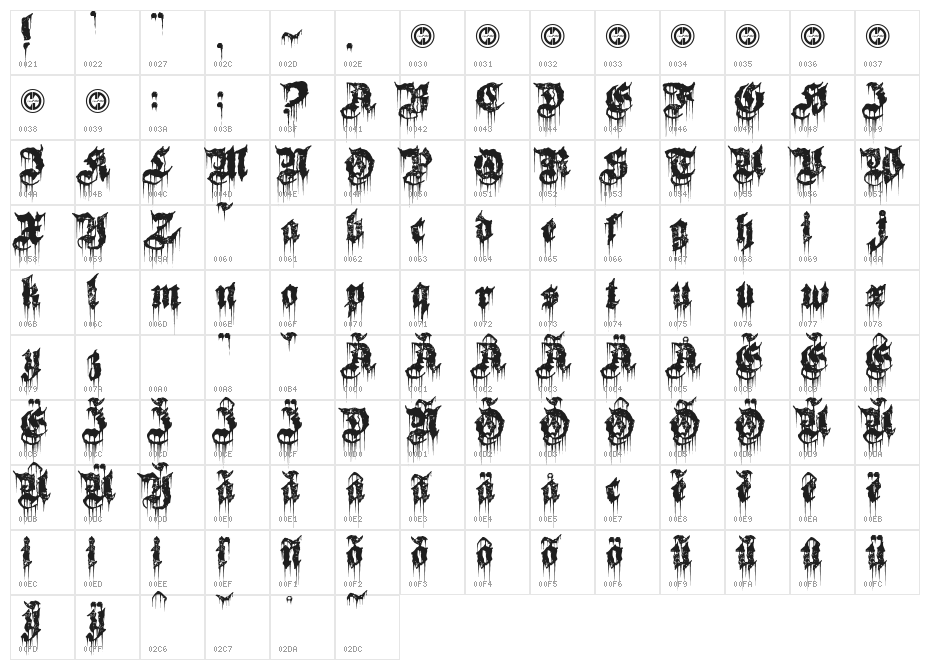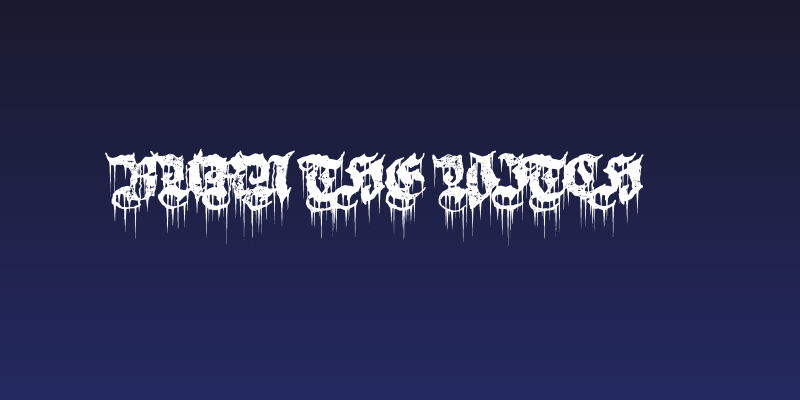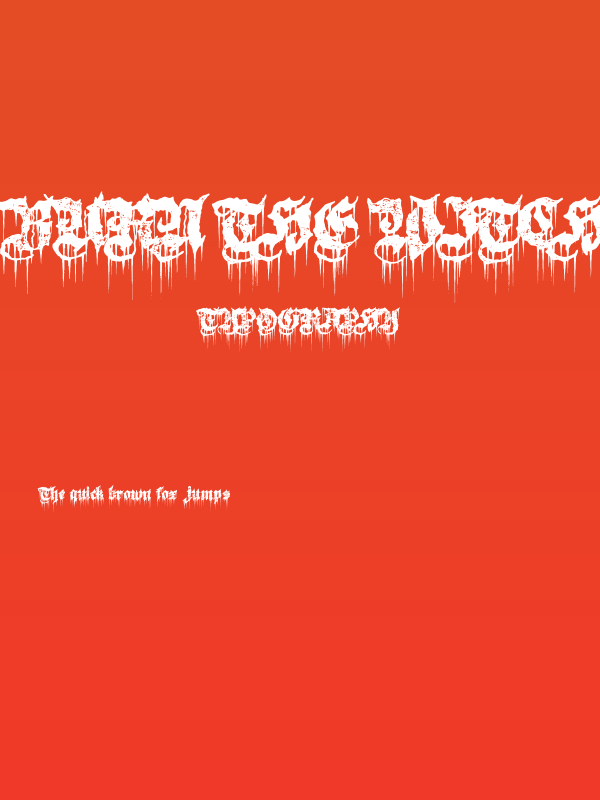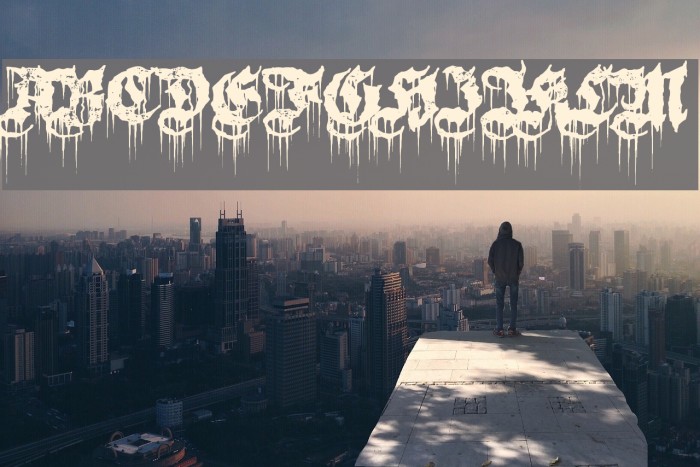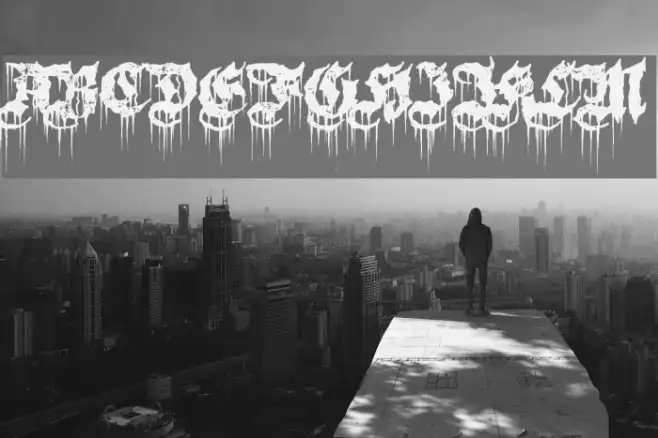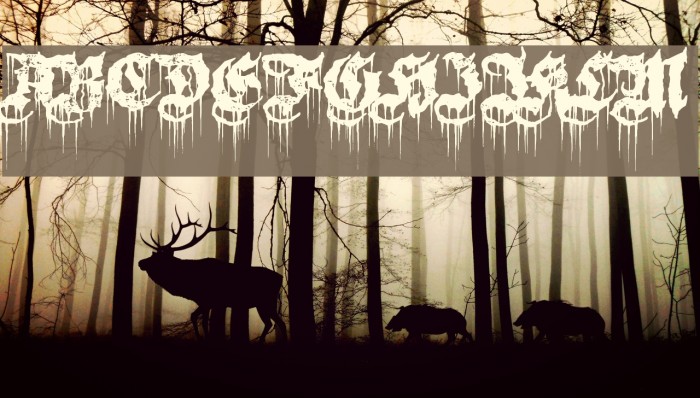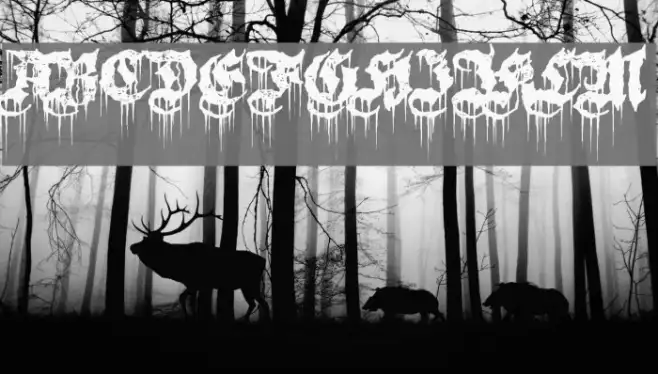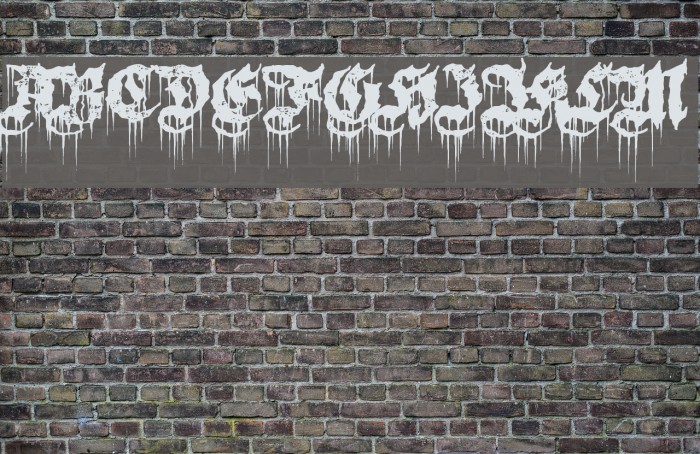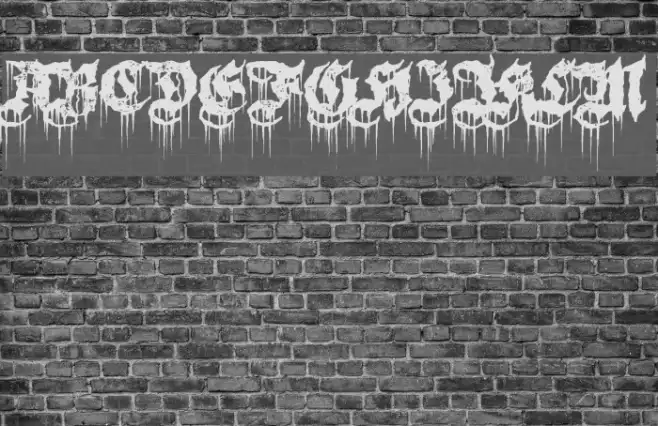
Burn The Witch Font
| Gesamtstil | Gothic, Decorative |
| Vorgeschlagene Projekte | Ideal for horror-themed posters, Halloween invitations, album covers for metal bands, or any project requiring a dark, gothic aesthetic. |